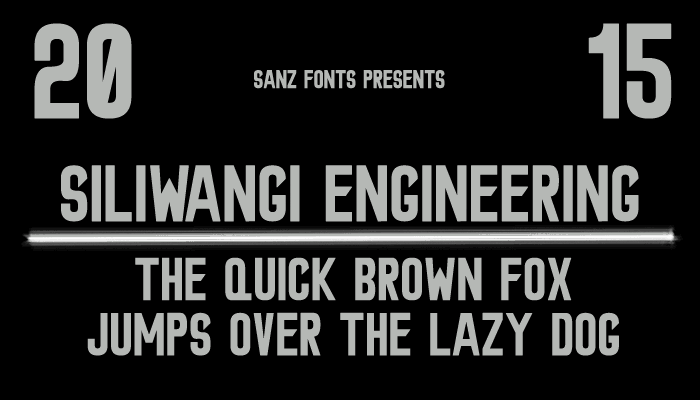
A Siliwangi Engineering Font é uma grata surpresa para quem busca uma fonte Blackletter que transborde com estilo e profundidade. Desenvolvida por Hamilton, esta escolha de fontes atinge diretamente a essência do trabalho técnico e acadêmico no Brasil. Seu design elegante e robusto destaca-se não apenas pela sua característica tipográfica única, mas também pelo seu ajuste perfeito aos textos técnicos complexos e notas acadêmicas. Com uma aparência sóbria e envolventemente sofisticada, a Siliwangi Engineering Font oferece um toque distinto para os projetos que exijem respeito por sua importância significativa. Seja ela usada em manuais de instruções técnicas ou capa de documentos acadêmicos, a fonte não apenas contribui com seu estilo distintivo, mas também demonstra uma cuidadosa atenção ao detalhe necessária para transmitir confiabilidade e autoridade.